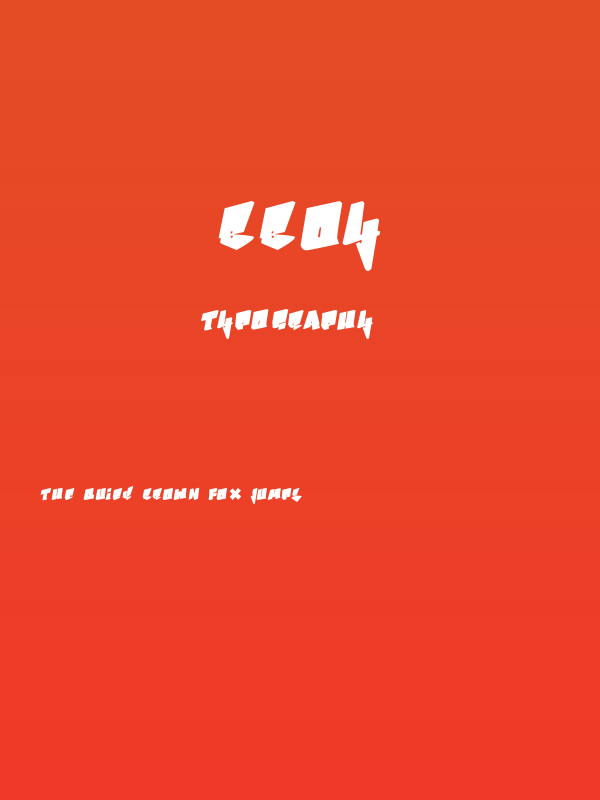
Bboy Font
✎ Decorative
| 分类 | Decorative |
| 整体风格 | Modern, Urban |
| 推荐项目 | Ideal for street art designs, urban-themed posters, music album covers, and edgy branding projects. |
| 作者 | Fonts by or from www.graffitifonts.net |